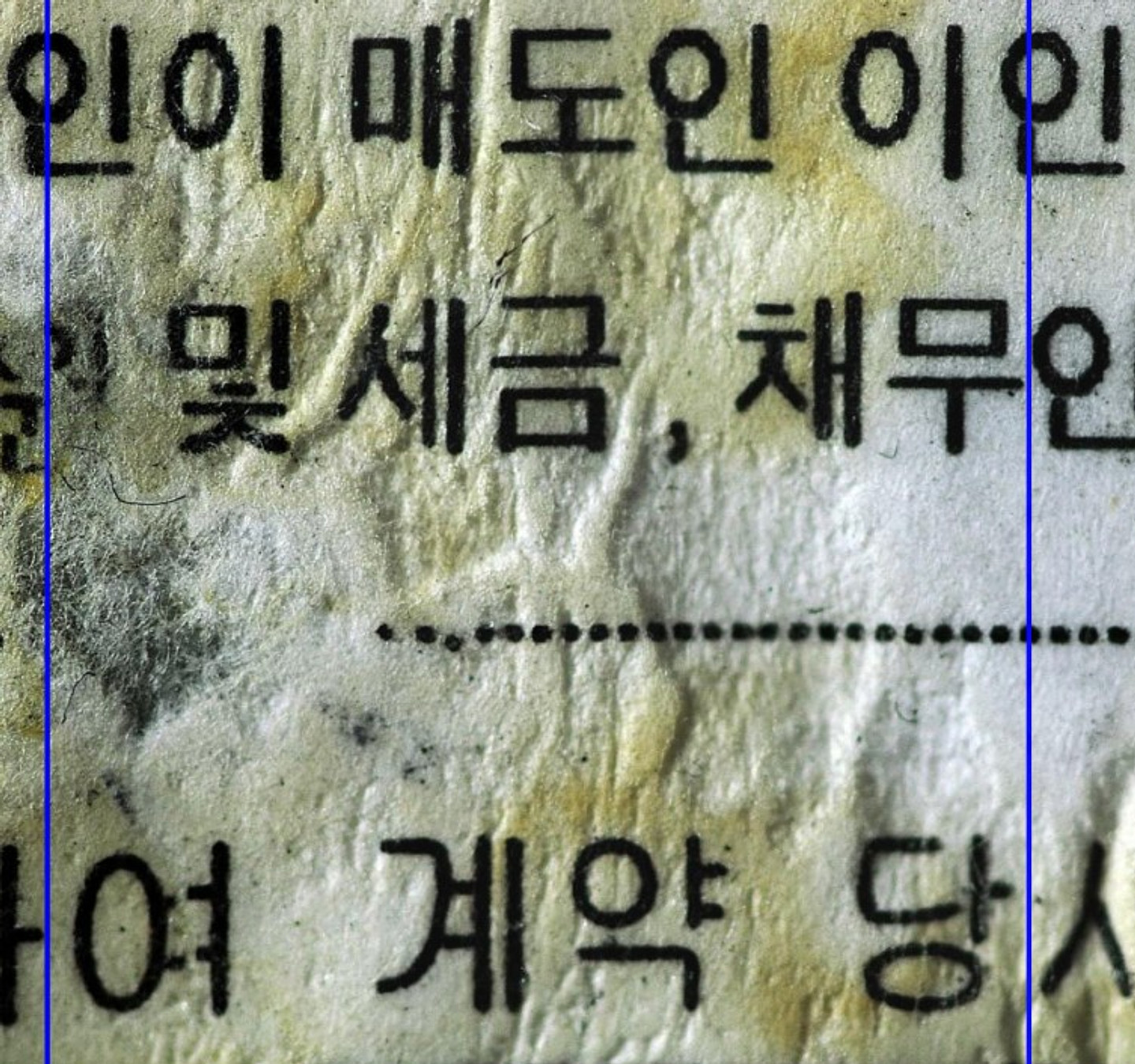
위조 문서 사용 폰트를 찾고 있습니다. 특징으로 "매"의 ㅁ이 그리고 "금"의 ㅁ이 돋음과 같이 생겼지만 돋음으로 설정했을 때 동일한 글자가 안나옵니다. 그리고 모든 "인"에서 이, ㄴ 받침이 거의 붙어있는 특징이 있습니다. 혹시 알고계신분 계시다면 꼭좀 알려주시면 감사하겠습니다